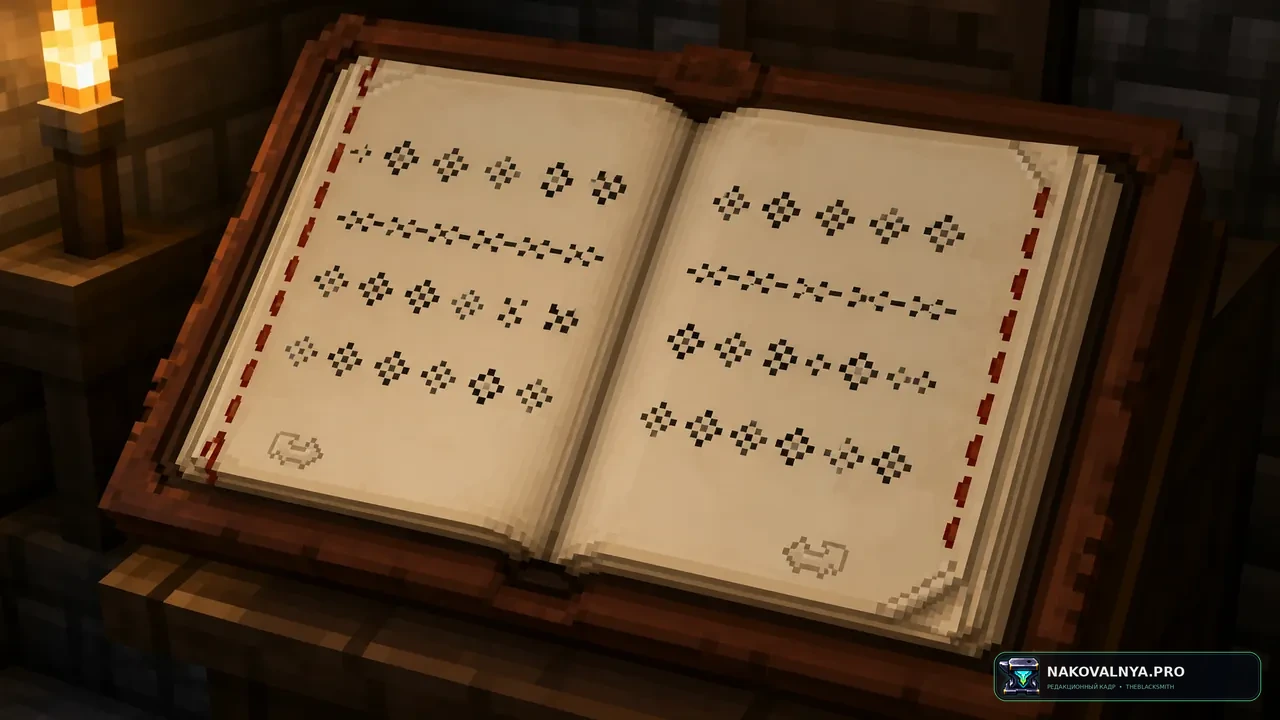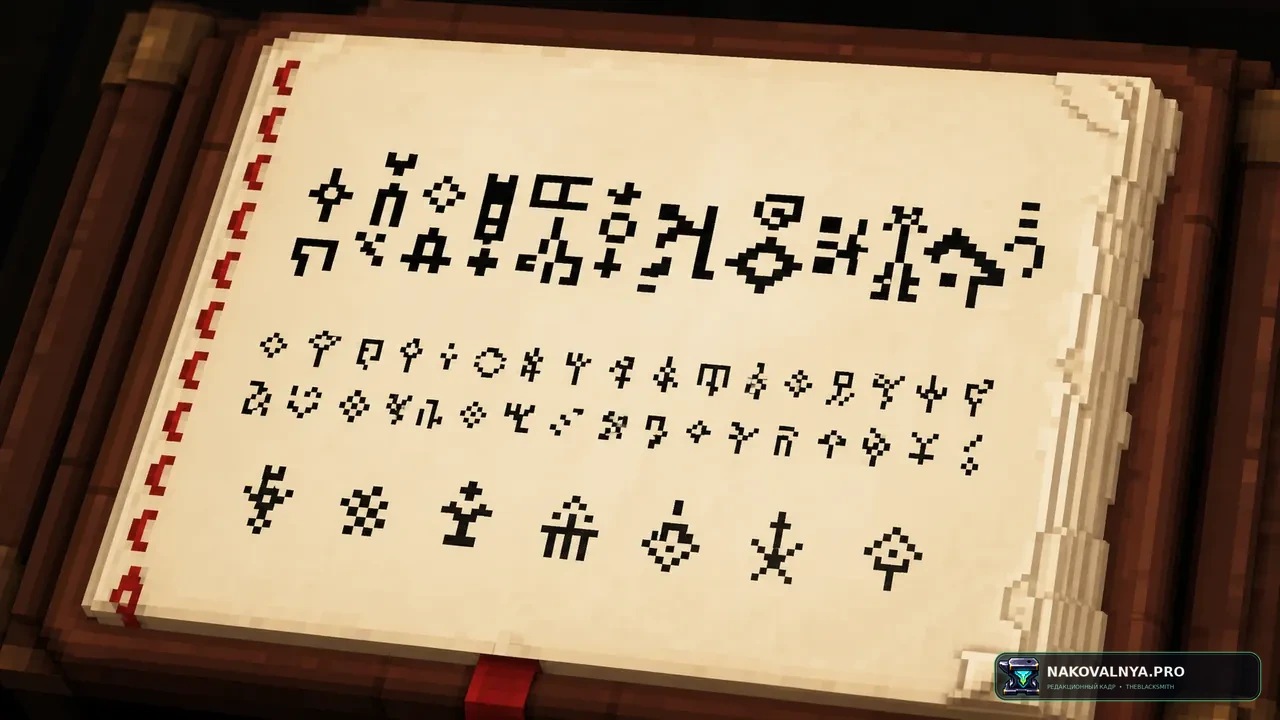
Ashen 16x Custom Font — текстуры на средневековый шрифт интерфейса в МайнкрафтеШрифт нарисован с нуля и задуман как цельная гарнитура, а не замена нескольких латинских букв. Он охватывает всё, что обычно можно набрать ванильными средствами, в том числе алфавит илладжеров и стандартный галактический алфавит стола зачарований. Засечки и средневековая пластика особенно органично смотрятся вместе с Ashen 16x, но дополнение отделено от него намеренно: его можно сочетать с другим визуальным паком. Такой подход меняет восприятие интерфейса и текста, не вмешиваясь в оформление мира.
Это точечный выбор для фэнтезийных сборок, карт и игроков, которым важна типографика интерфейса. Он не подойдёт желающим преобразить блоки и предметы либо получить гарантированную замену каждого Unicode-символа.
Ванильный набор, включая алфавит илладжеров и стандартный галактический алфавит.
Пак не перекрывает часть знаков, которые игра вставляет как Unicode, например деванагари.